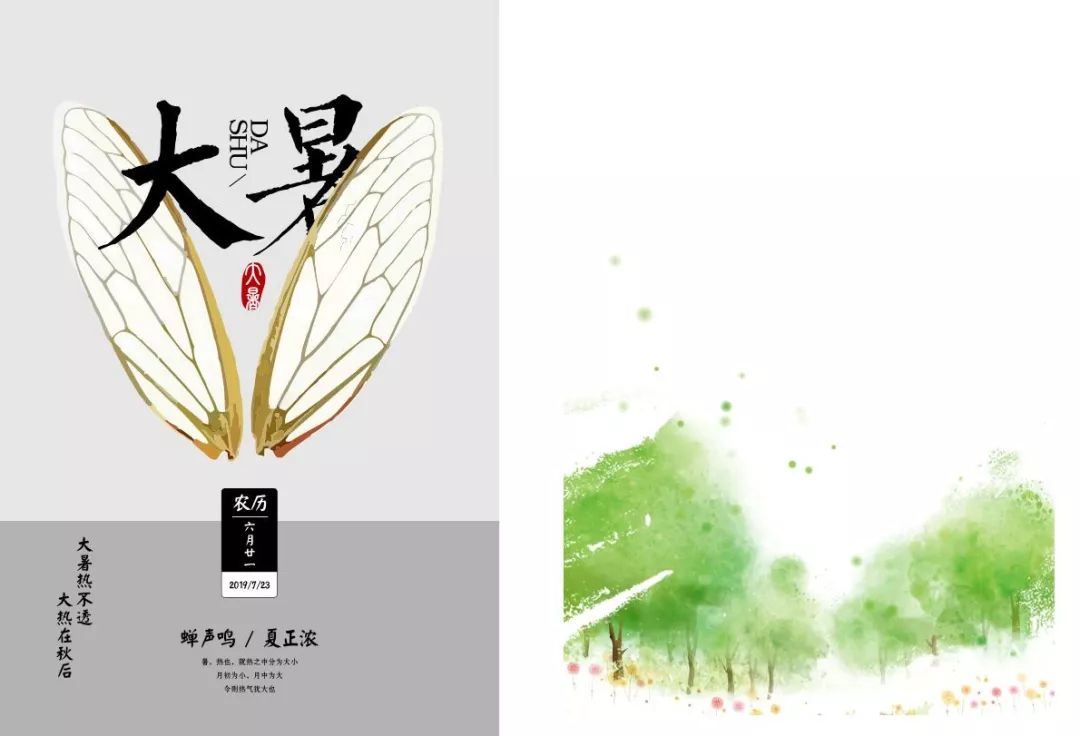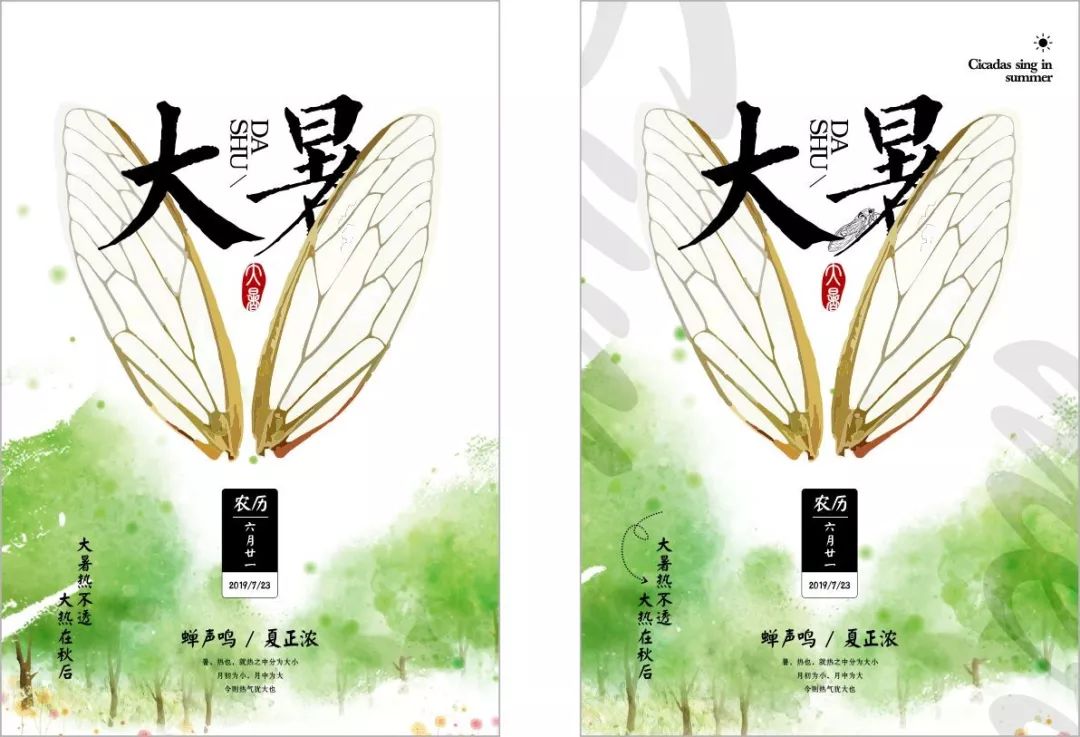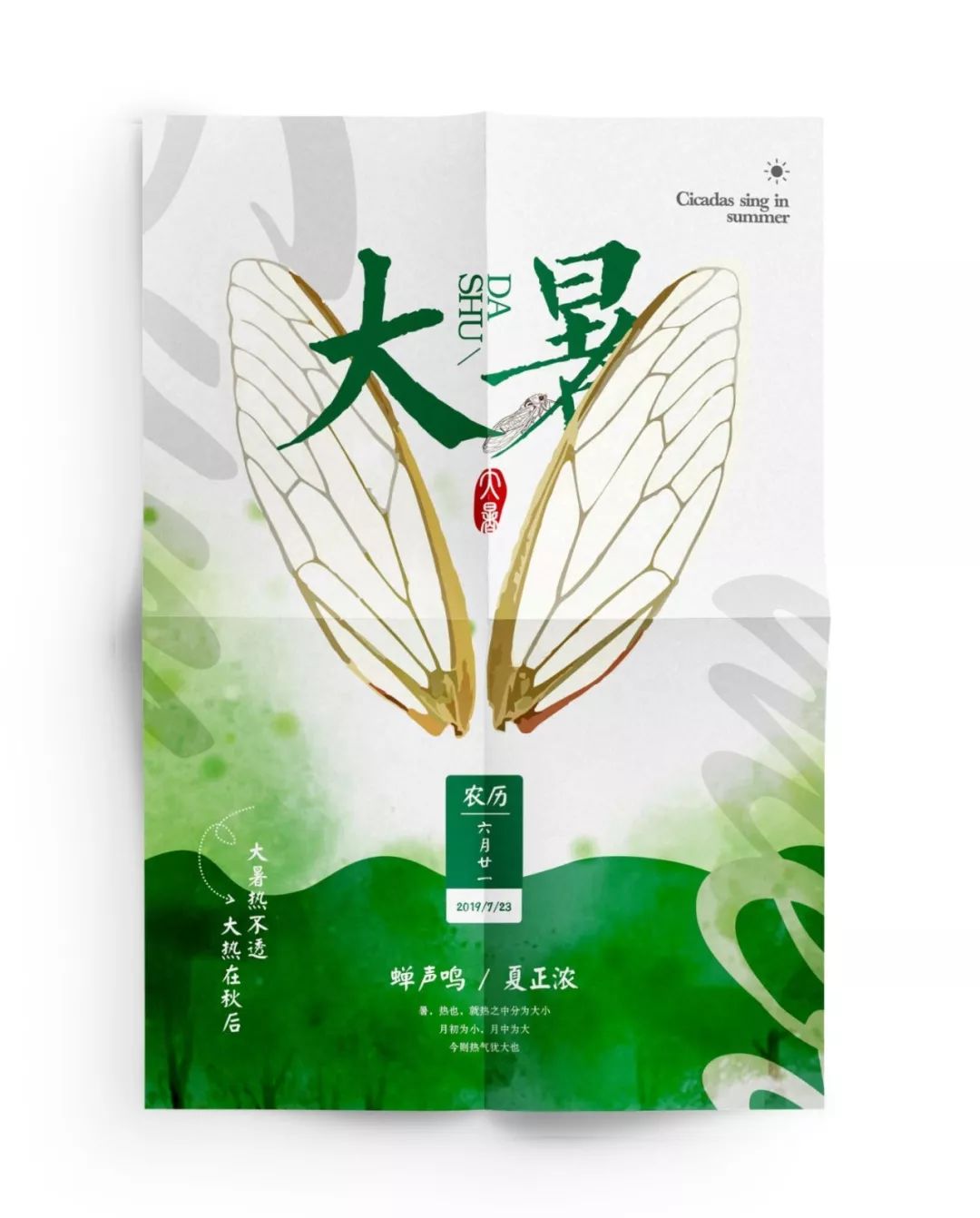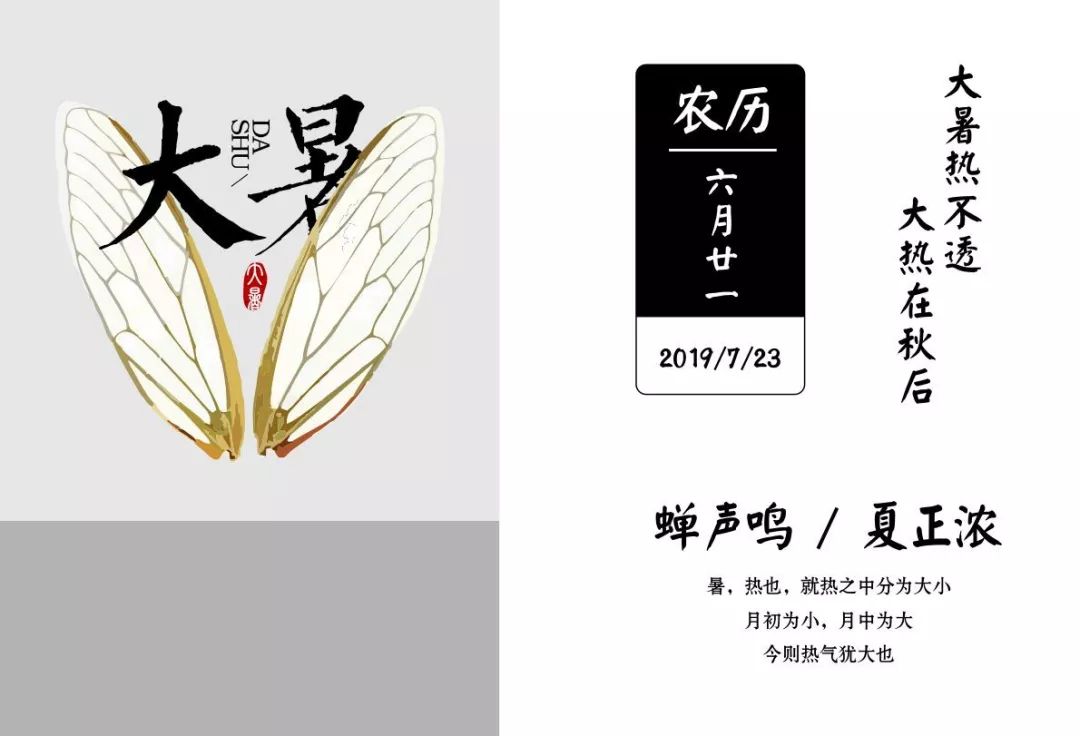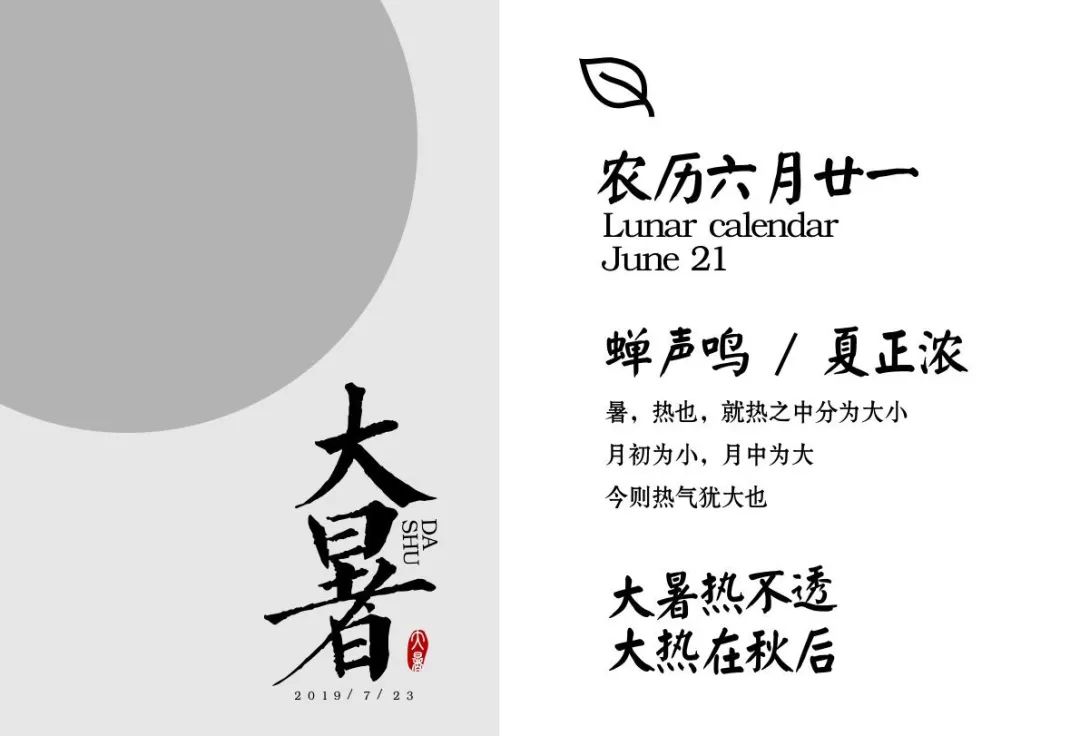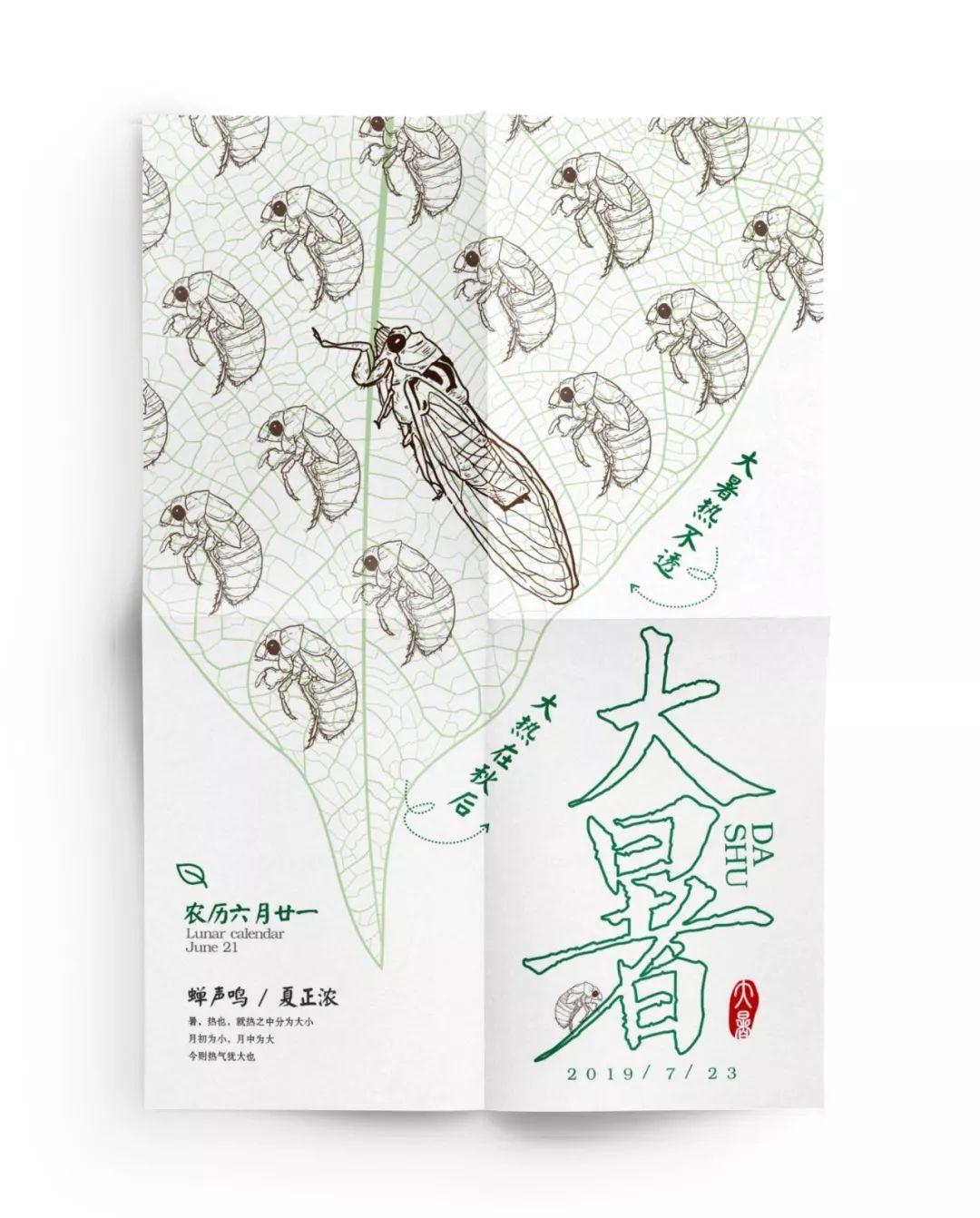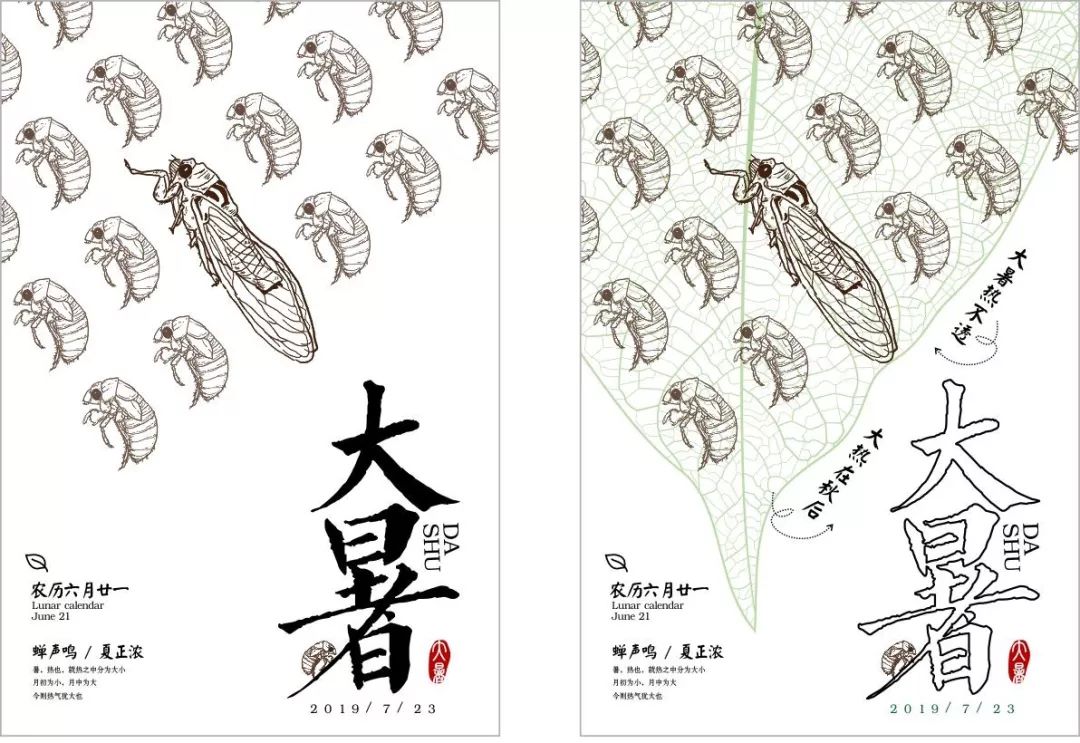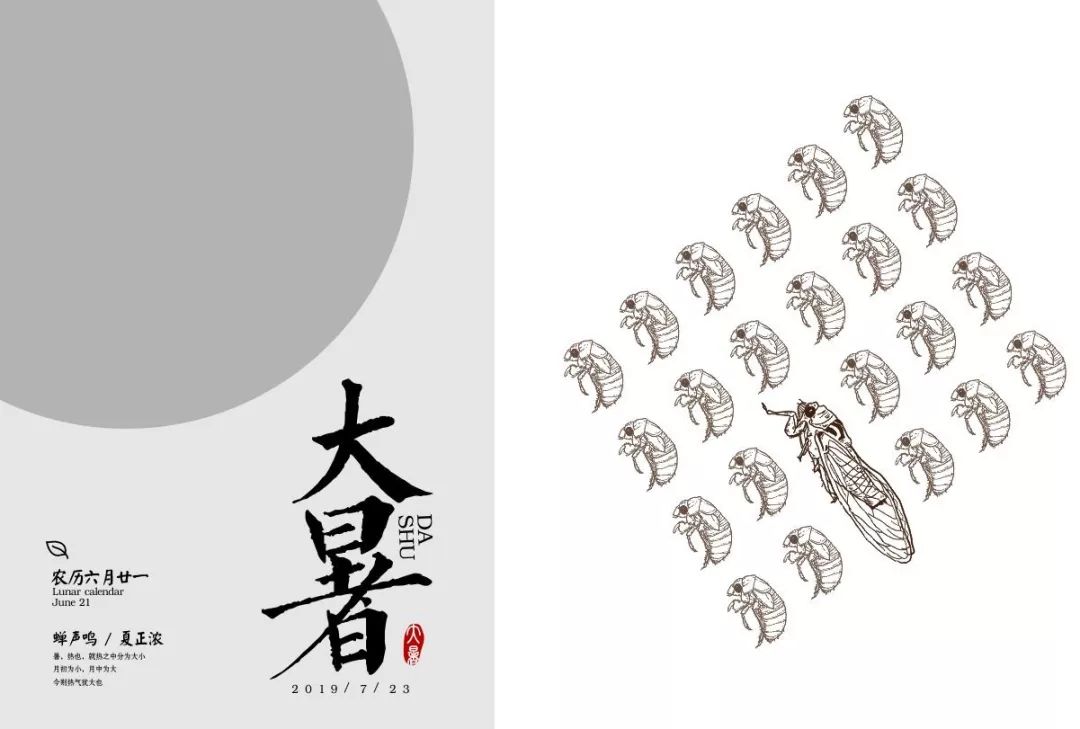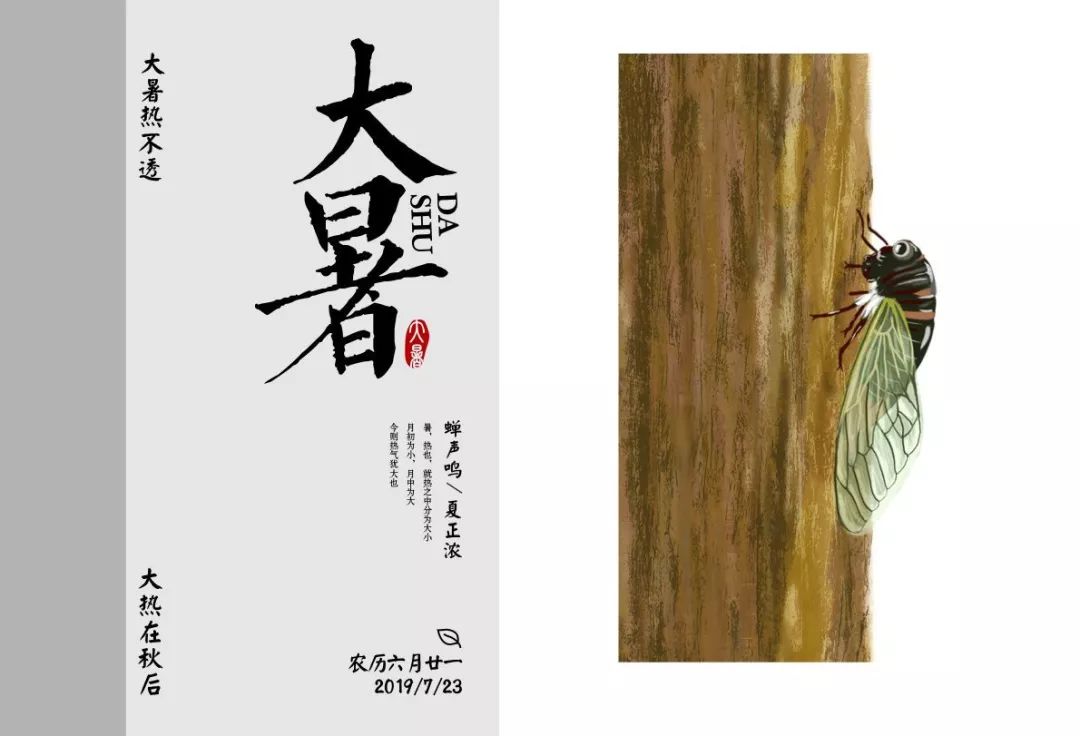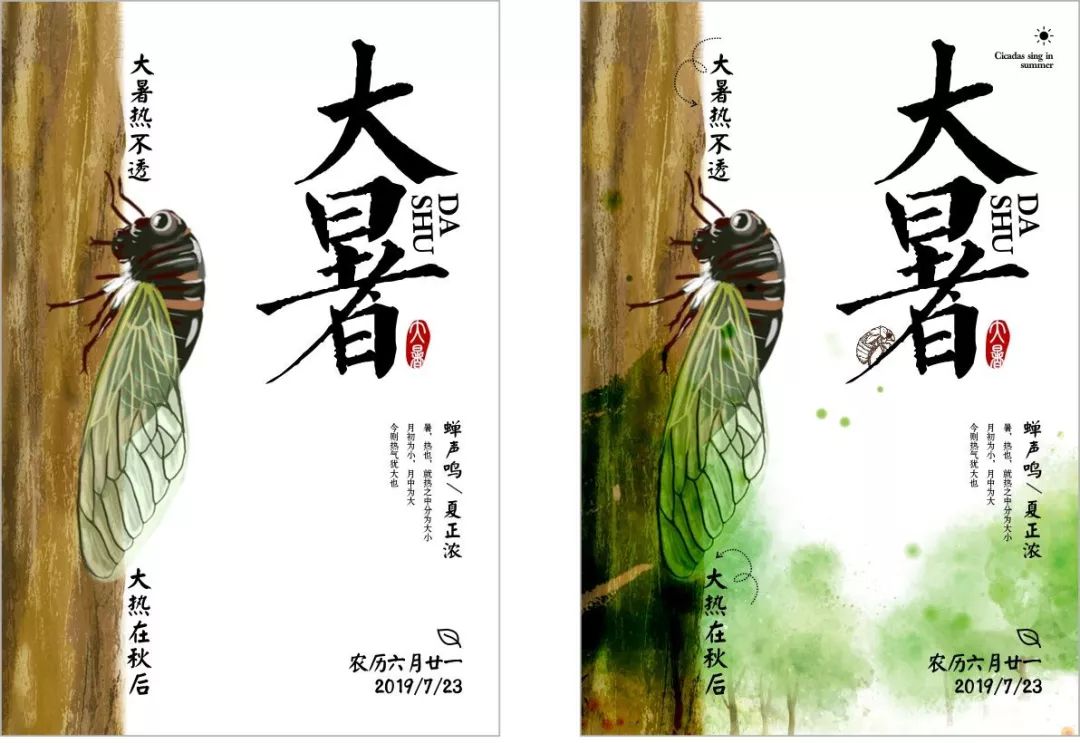
我抱着空调,做了张大暑的海报
Bingo!有咯,蝉代表着神魔,夏天,酷暑,这不大暑就要到了吗,就来用大暑做一个设计咯,拉着M君急匆匆跑回公司,打开电脑,赶紧来张海报。
啦啦啦啦,疯狂整理完内容,W君要开始做设计咯
我们先用上下分割来做一个版面,说到蝉呢,W君就想到了千里之外,那薄如蝉翼的未来,经不起谁来拆...(后面你们来唱),那么就找来一个蝉翼,与主标题做个结合,放到画面中,按比例分割下版面,下方需要放内容的区域用灰色色块代替,再将其他信息做一个规范。
我们刚才整理好的信息都放入到画面中,看画面中哪里空间有问题,我们就来拿信息解决。我们再来找一个夏天的背景。
我们将背景放到画面中的,然后提取信息对细节进行一些优化。同时找一只小知了(我拍的不好看,做不了素材o(╥﹏╥)o)我们把小知了就放到暑字上面,让观者知道是蝉翼,这一步大家要好好看看哦。
来,然后我们做个色彩搭配,底部加个色块叠加一下,再做个海报样机,噔噔噔噔~第一个画面就完成啦。
我们现在来做第二个版面,这次我们来用对角构图做一个版面,我们还是对文字主标题做一个编排,放到画面中,左上方灰色区域代表图片素材的位置,然后对内文做个编排。
我们再将内文文字都放入到画面中,同时在网上搜索相关的素材,这次我们来做的有趣点,知了是不是变身过来的,我们来找个它的原始形态,做个特异构成(密集恐惧者慎看(。・ω・。))
我们将素材占据画面中灰色色块区域,然后找一个大叶子承载这些小动物,提取信息对细节进行一些优化。再把刚才漏掉的“大暑热不透,大热在秋后”沿着叶子路径摆放,主标题也用线描的形式与主体相呼应。
我们再来做个色彩搭配,做个海报样机,嘟嘟嘟嘟~第二个画面就完成啦。
我们最后再来做一个版面,这次我们来用左右构图做一个版面,直接将上一张排好的主标题拉过来(我还是比较懒),左方灰色区域为图片素材,然后对内文做个编排。
接着我们将内文文字都放入到画面中,同时网上找个蝉的素材,咦,刚好发现一个合适的。
我们将素材放到画面中,刚好蝉还能做个破图,美美哒。之后我们再将画面进行优化,找一些小元素来丰富画面。
我们再来做个色彩搭配,做个海报样机,biubiubiu~第三个画面就完成啦,呼呼呼,终于做完了,来个西瓜,解解暑。